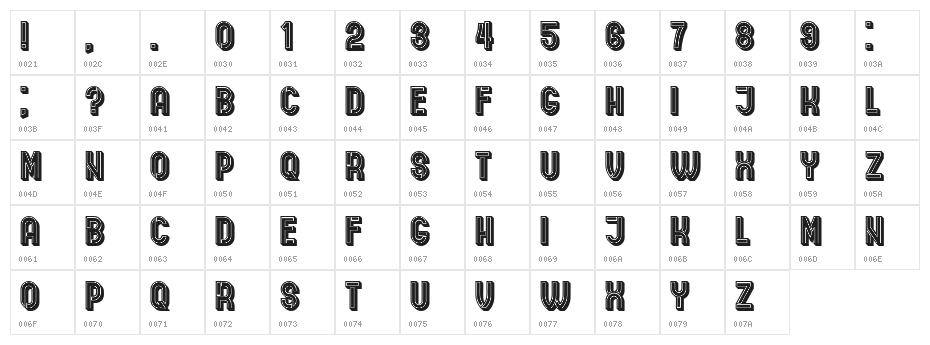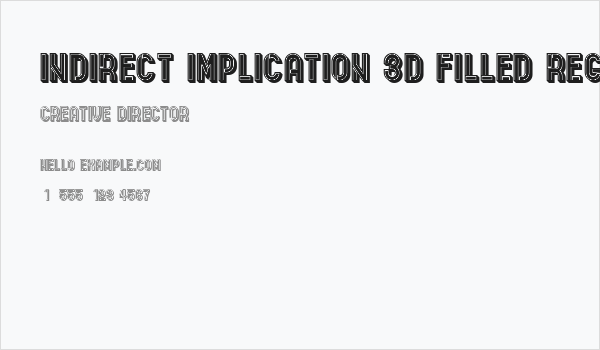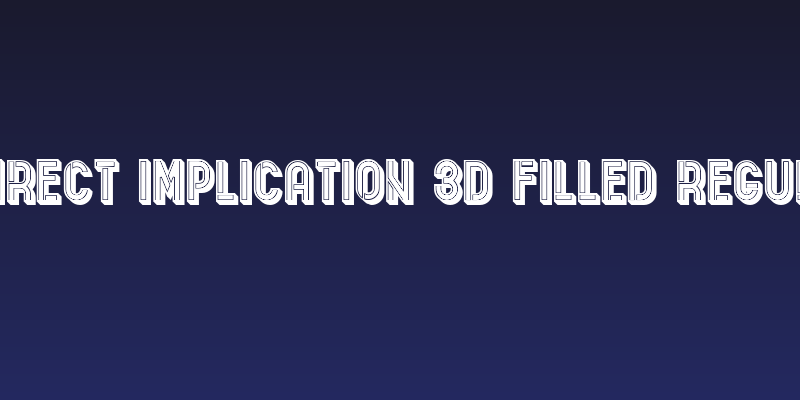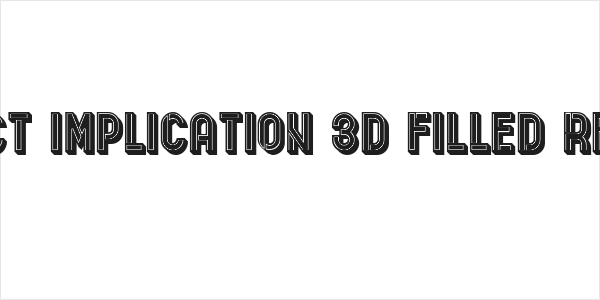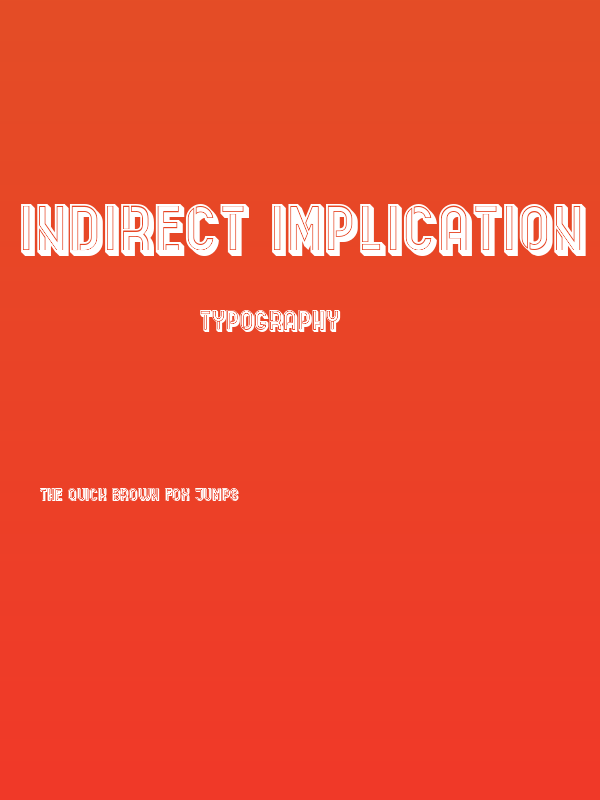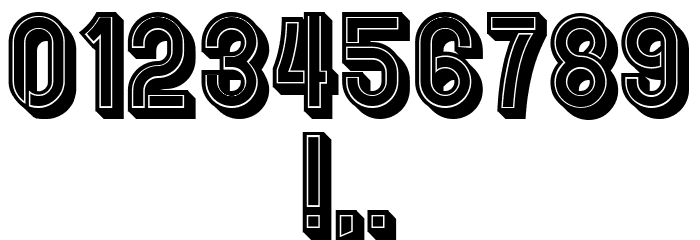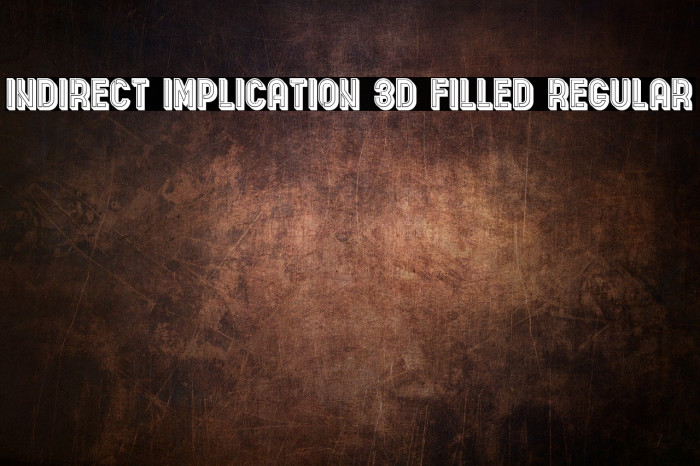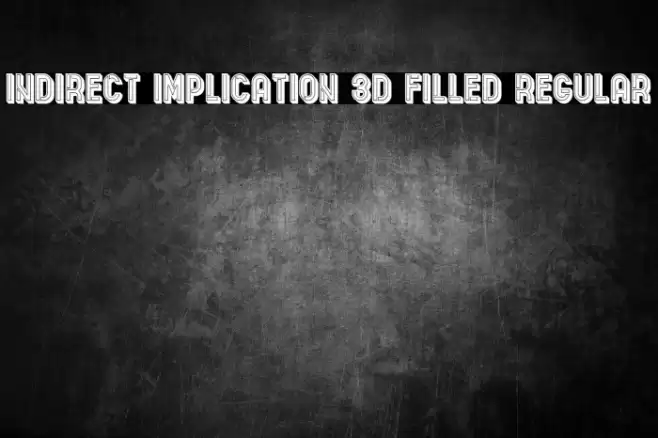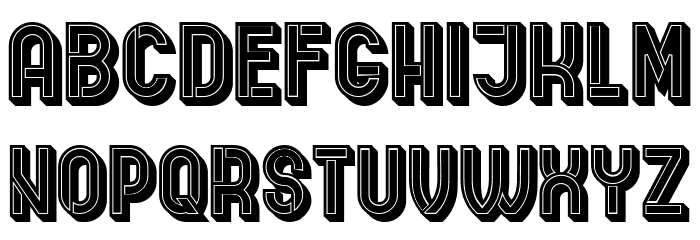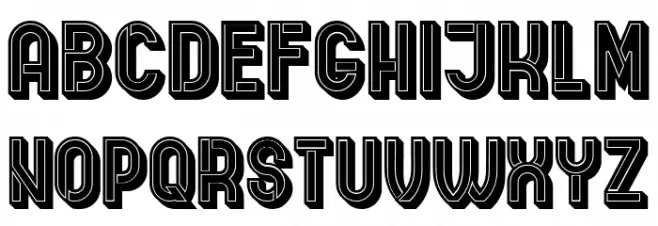
Indirect Implication 3D Filled Regular Font
| Projetos propostos | Ideal for posters, advertisements, video game titles, and any project requiring a bold, attention-grabbing typeface. |